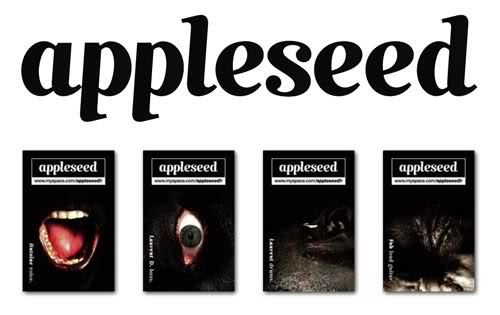
Unformale Kursive gesucht
Liebe Typos
Wie andere bin ich auf der Suche nach einer bestimmten Schrift. Es handelt sich um die verspielte Kursive, die im beiliegendem Poster (?) verwendet wird.
Habe versch. klassizistische Familien angeschaut, ohne Erfolg.
Vielleicht gibt es unter euch einen Krack der zu helfen weiss.
Unglaublich wie schnell man hier eine Antwort auf einer solchen Frage bekommt. Es scheint sich genau um die Schrift Mimix zu handeln. Ich sehe sogar, dass eine Gratis-Version der Schrift vorhanden ist: http://www.mimix.ch. Ich lade sie mir gleich hinunter und probiere sie aus.